Letter Space Free fontsでは手描き風のフォント7種類をダウンロードできます。
いずれも個性があって、クオリティもいい感じです。
ラフな雰囲気を出したい時などに使えます。
NettelBladt
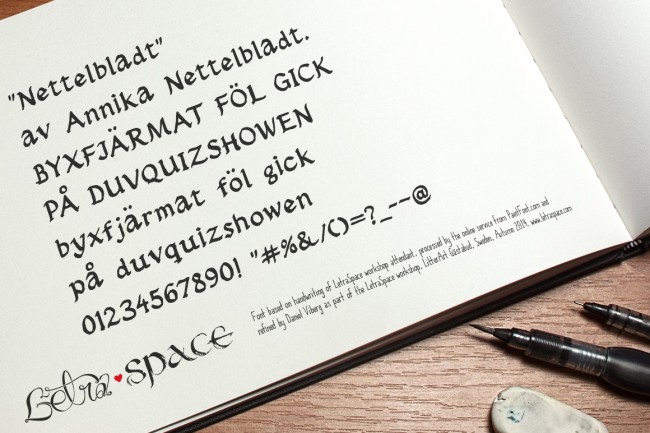
Kickart
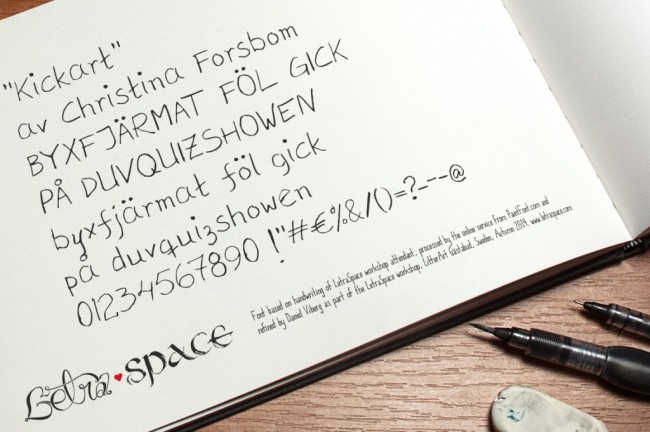
Gagfi
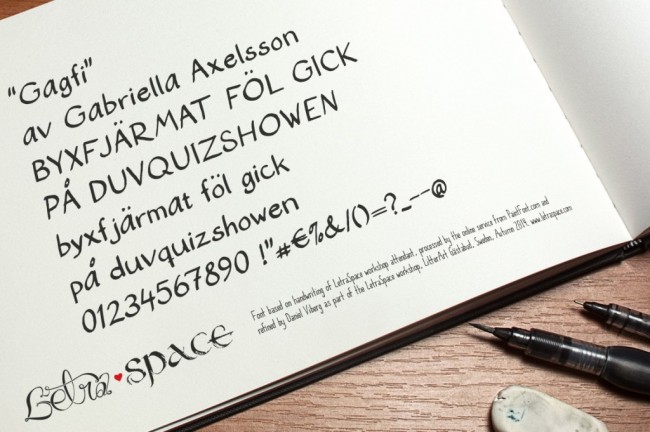
Dayweed
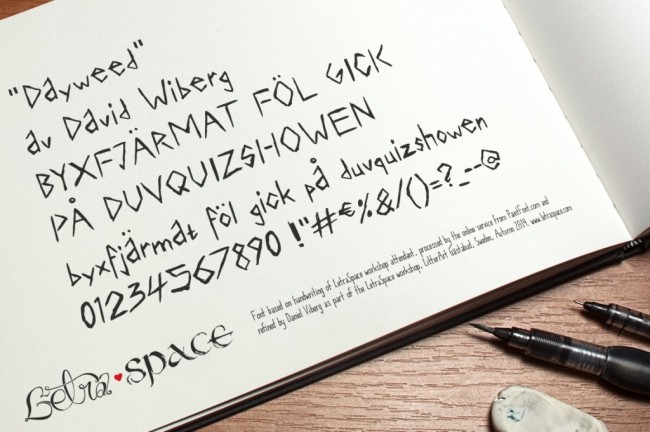
Humafi
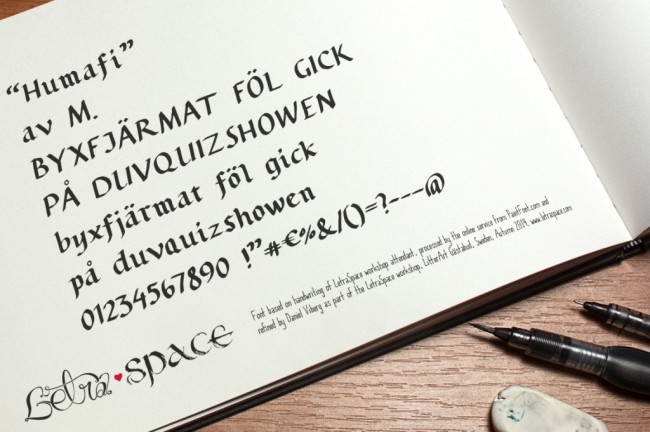
Tyra
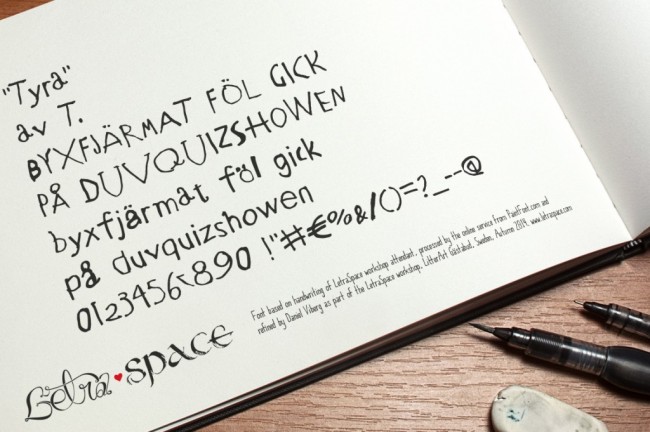
Miranda